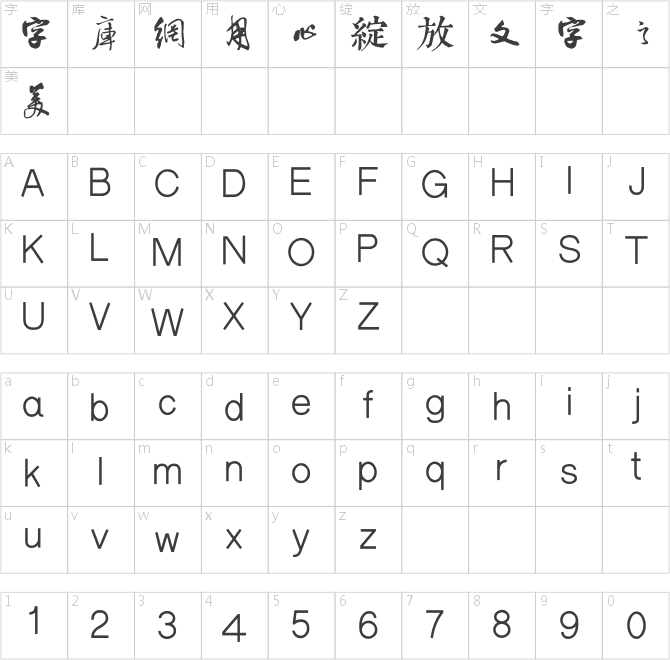
字體名稱: 邯鄲王鐸千字文
邯鄲王鐸千字文
邯鄲王鐸千字文字體下載邯鄲(清)王鐸千字文
王鐸(1592年—1652年),字覺(jué)斯,一字覺(jué)之,號(hào)十樵、嵩樵, 又號(hào)癡庵、癡仙道人,別署煙潭漁叟,河南孟津人  。明末清初書(shū)畫(huà)家 。他的書(shū)法與董其昌齊名,有“南董北王”之稱  。北京大學(xué)教授、引碑入草開(kāi)創(chuàng)者的李志敏評(píng)價(jià):“王鐸的草書(shū)縱逸,放而不流,縱橫郁勃,骨氣深厚”。明天啟二年(1622年)中進(jìn)士,受考官袁可立提攜,入翰林院庶吉士,累擢禮部尚書(shū)。崇禎十六年(1643年),王鐸為東閣大學(xué)士。
崇禎十七年(清世祖順治元年,1644年)滿清入關(guān)后被授予禮部尚書(shū)、官弘文院學(xué)士,加太子少保。
清順治九年(1652年)病逝故里。享年六十一歲,葬于河南鞏義洛河邊,謚文安。
王鐸的書(shū)法作品有《擬山園帖》和《瑯華館帖》等,其繪畫(huà)作品有《雪景竹石圖》等。